1. Erica One – Extravagante
Perfecta para: títulos de eventos, pósteres artísticos, logos creativos
Con sus curvas irregulares y su aspecto un poco retro, Erica One capta la atención desde el primer vistazo. ¡Tiene mucha personalidad!
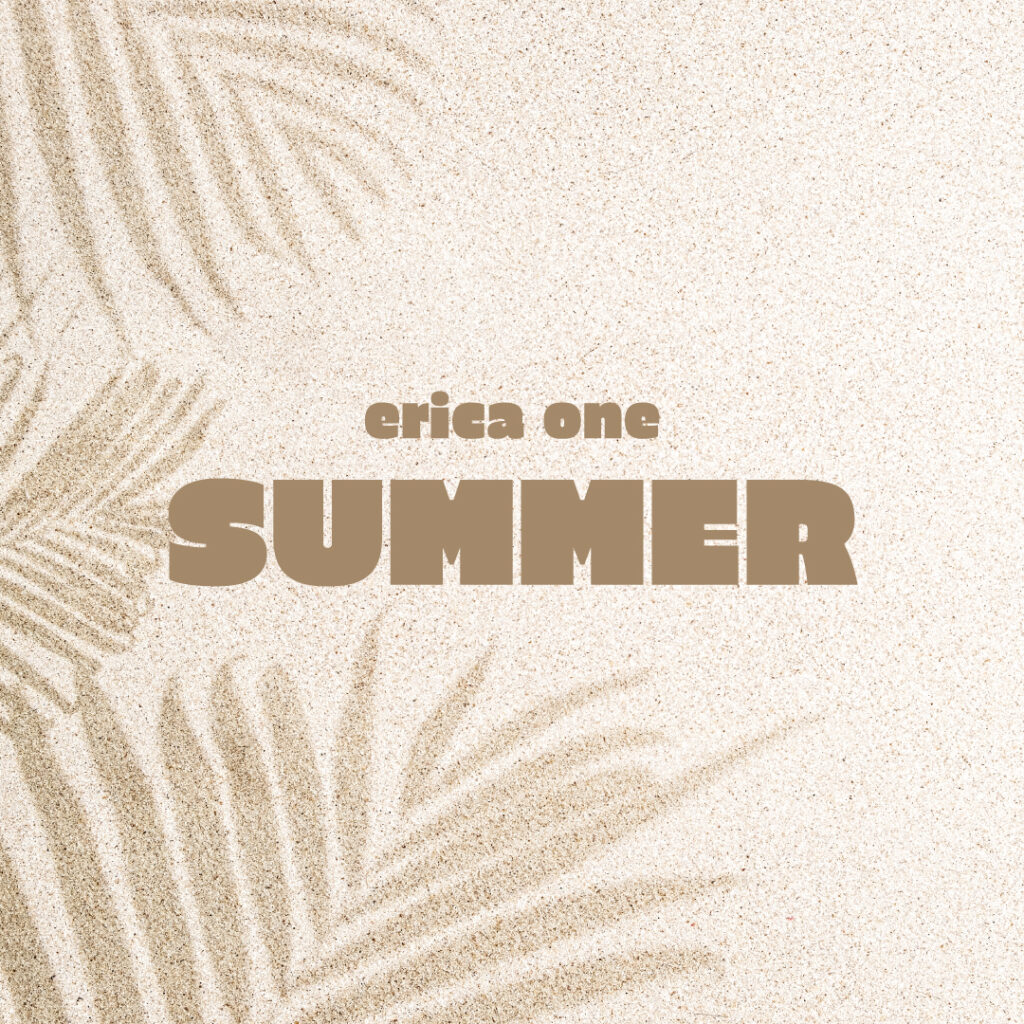
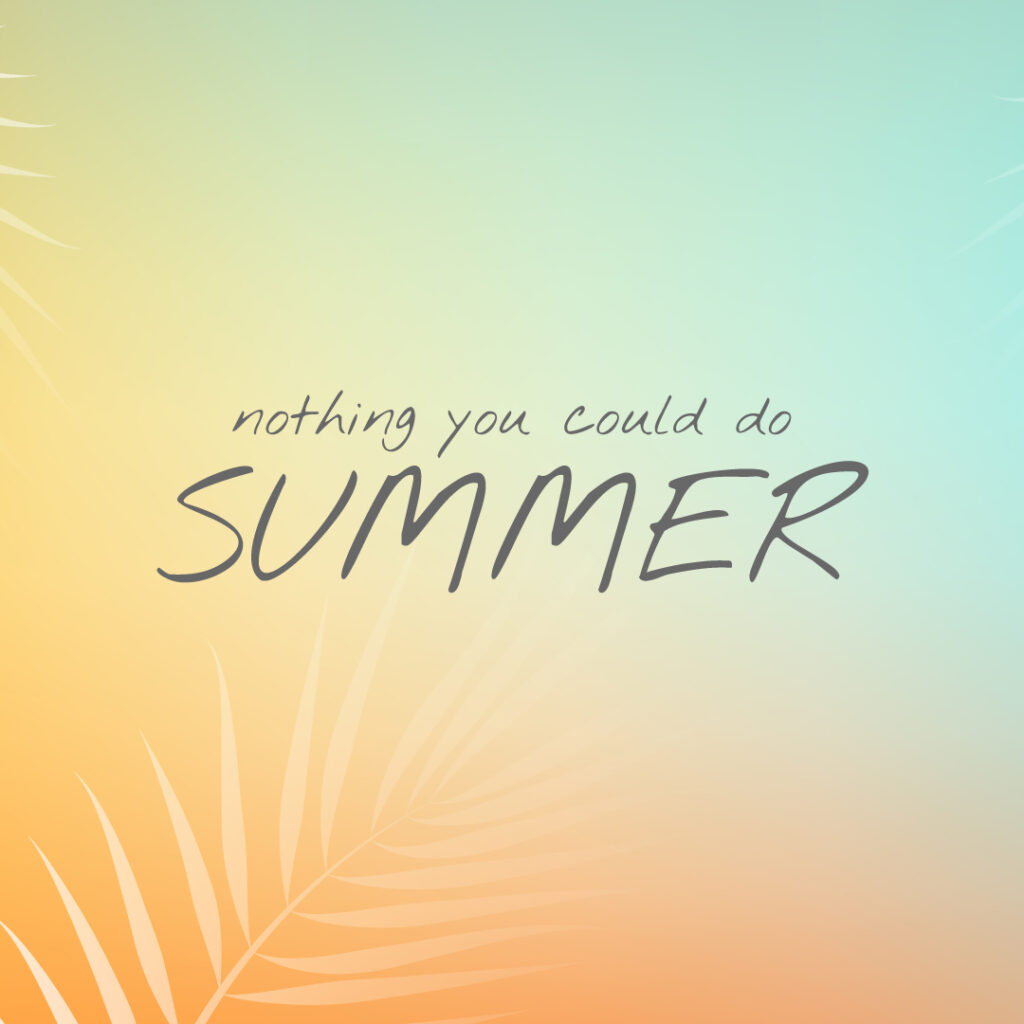
2. Nothing You Could Do – Letra a mano
Perfecta para: tarjetas postales, papelería, firmas manuscritas
Una tipo manuscrita natural y fluida, como una nota garabateada junto al mar. Ideal para aportar un toque humano.
3. Barlow Condensed – Deportiva y dinámica
Perfecta para: pósteres de gran formato, soportes de gran formato, títulos llamativos
Compacta, moderna y muy legible, Barlow Condensded aporta ritmo a tus diseños manteniendo un estilo limpio y ordenado.
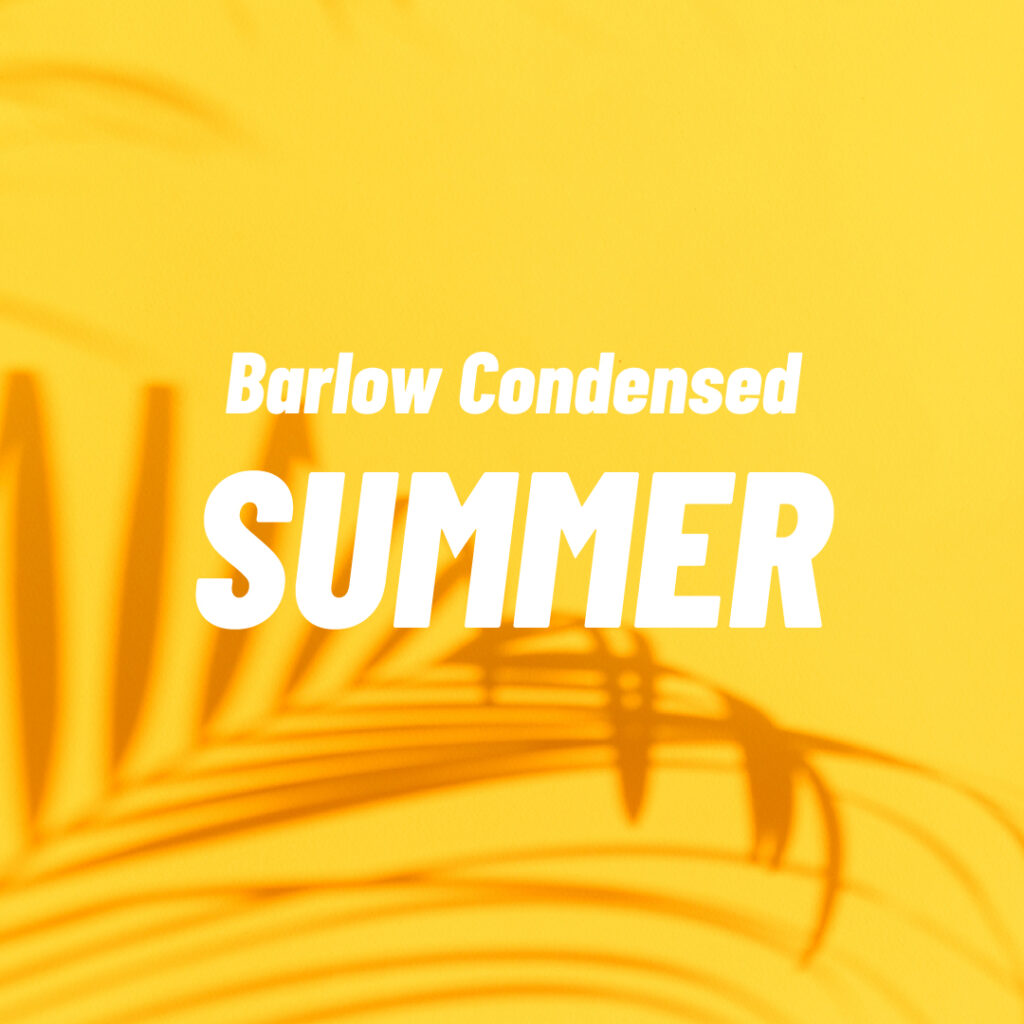
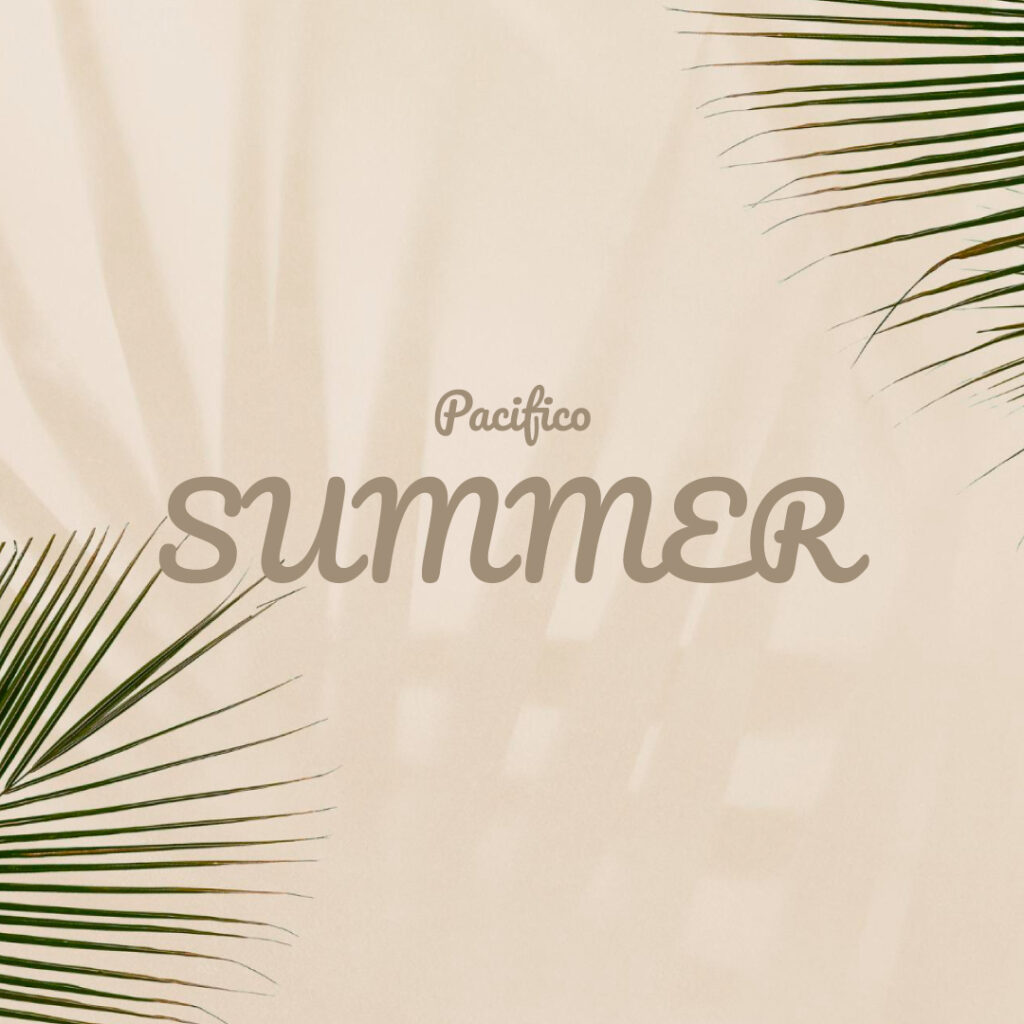
4. Pacifico – Muy veraniega
Perfecta para: comida, lifestyle, branding casual
Inspirada en los letreros retro de California, Pacifico transmite buen rollo al instante. Ideal para una identidad de marca con estilo feel-good.
5. Bungee – La tipografía que rompe
Perfecta para: pósteres urbanos, gran formato, títulos divertidos
Con su estilo en negrita y vertical, Bungee está hecho para destacar. Perfecta para exteriores y grandes formatos.
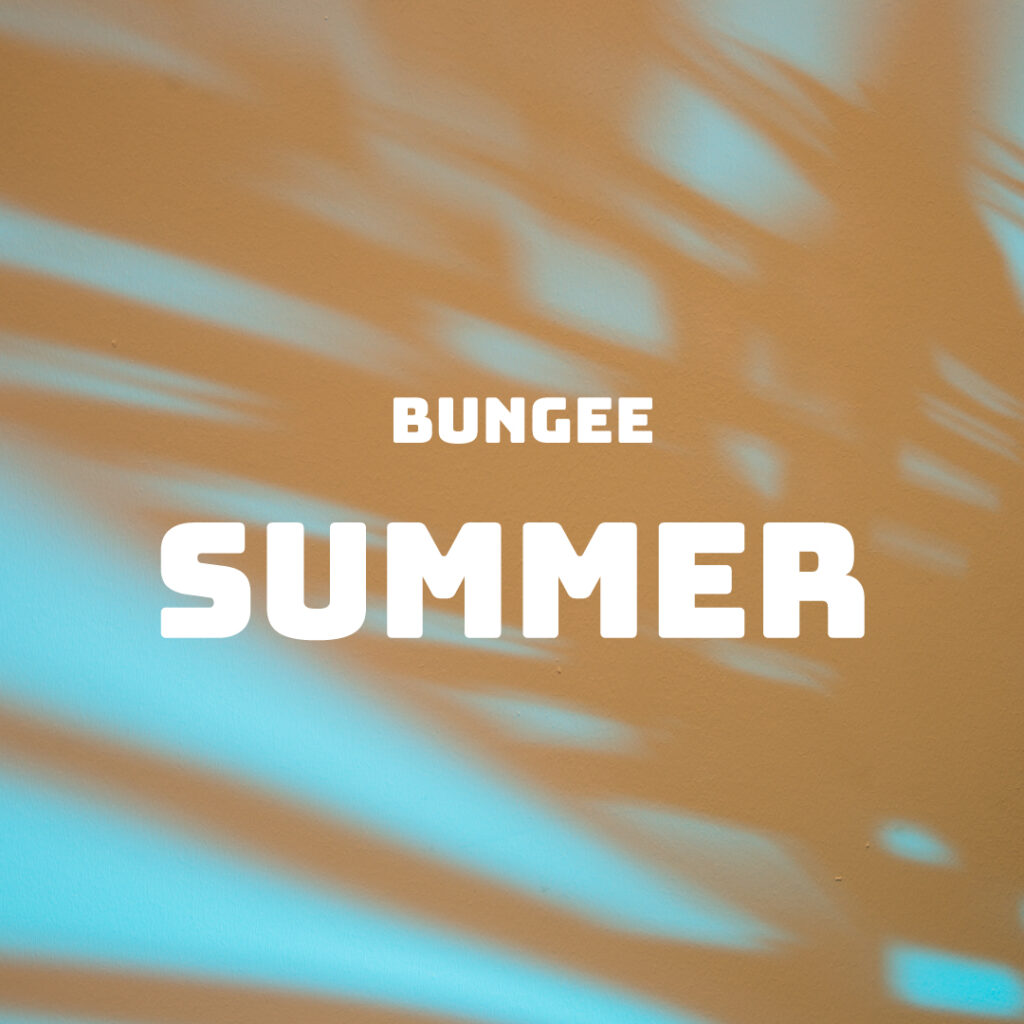
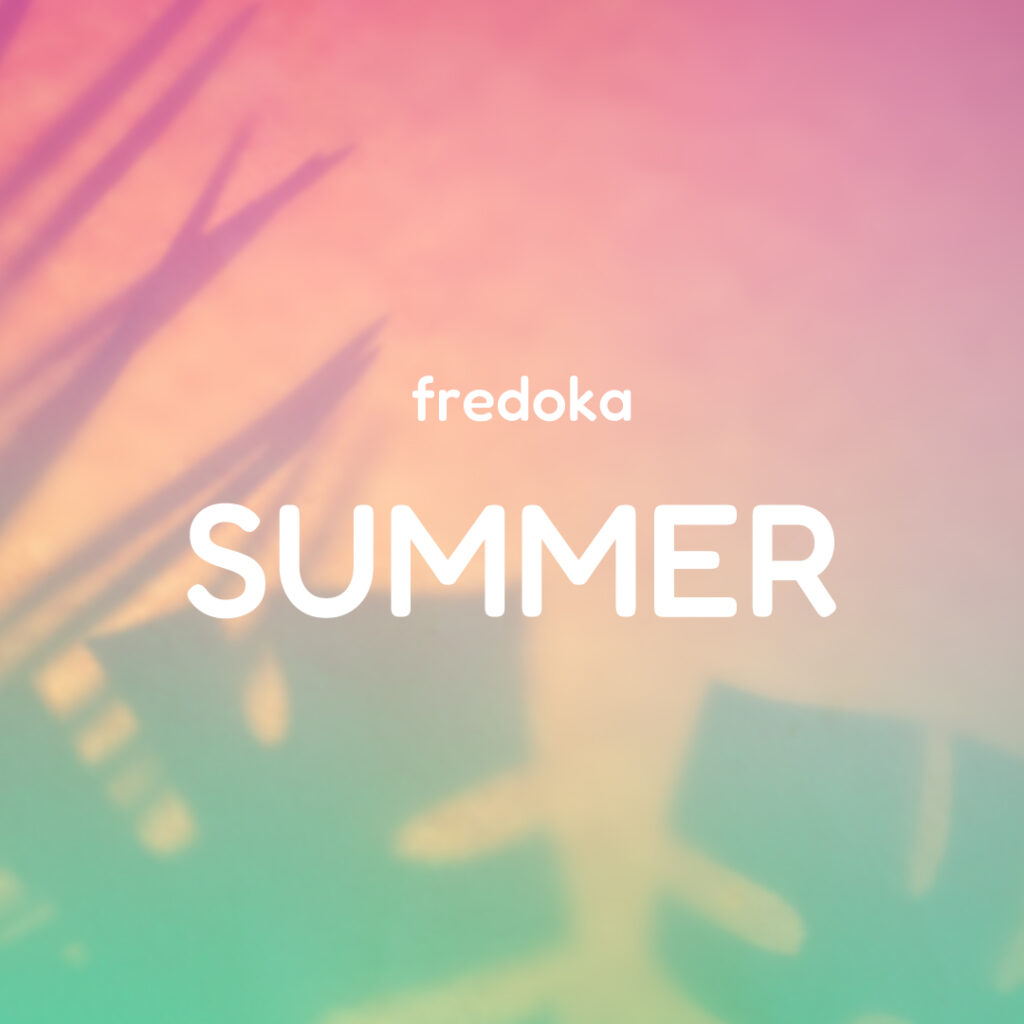
6. Fredoka – Redonda y accesible
Perfecta para menús, identidad visual de comida, comunicación infantil
Con sus letras redondeadas, Fredoka transmite cercanía y simpatía. Además, se lee perfectamente tanto en pantalla como en formato impreso.
7. Shrikhand – Atrevida
Perfecta para: branding original, packaging, pósteres de festival
Entre lo vintage y lo cartoon, Shrikhand tiene una presencia gráfica única. Por sí sola, viste cualquier título.
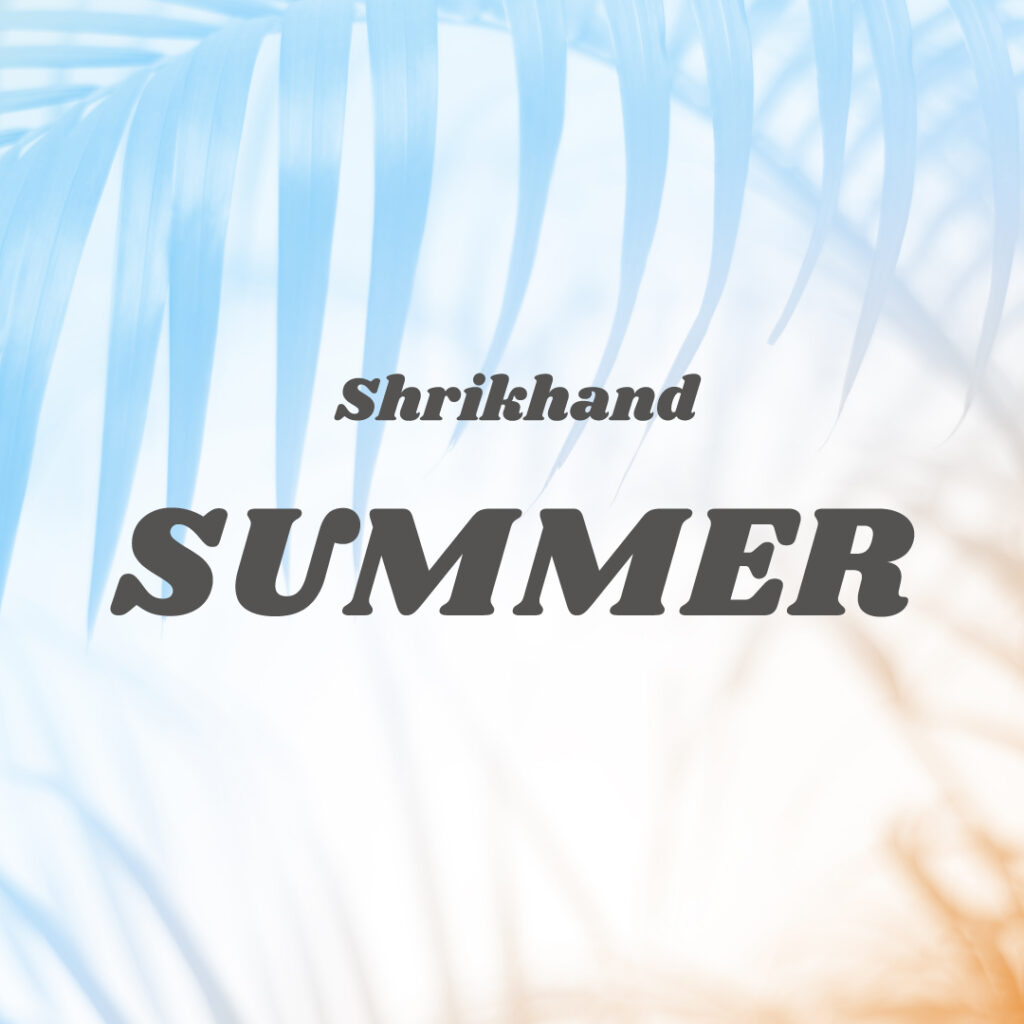
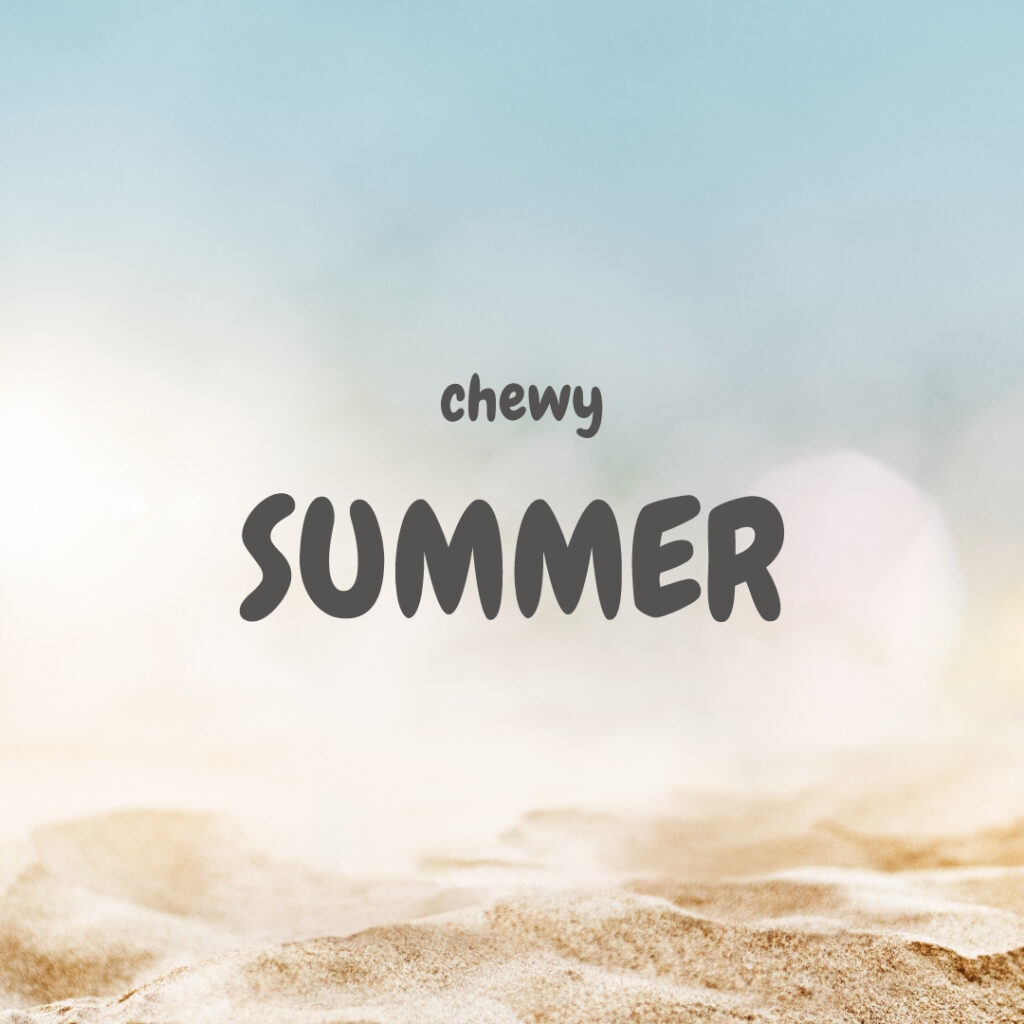
8. Chewy – Golosa
Perfecta para: snacks, helados, restaurantes familiares
Inspirada en tipografías de comics, Chewy es lúdica, generosa y alegre. Para usar sin moderación en tus creaciones veraniegas.
9. Poiret One – Elegante
Perfecta para: papelería elegante, diseño editorial, comunicación de eventos
Fina y minimalista, Poiret One ofrece un estilo que combina lo retro con lo sofisticado. Aporta mucho con muy poco.
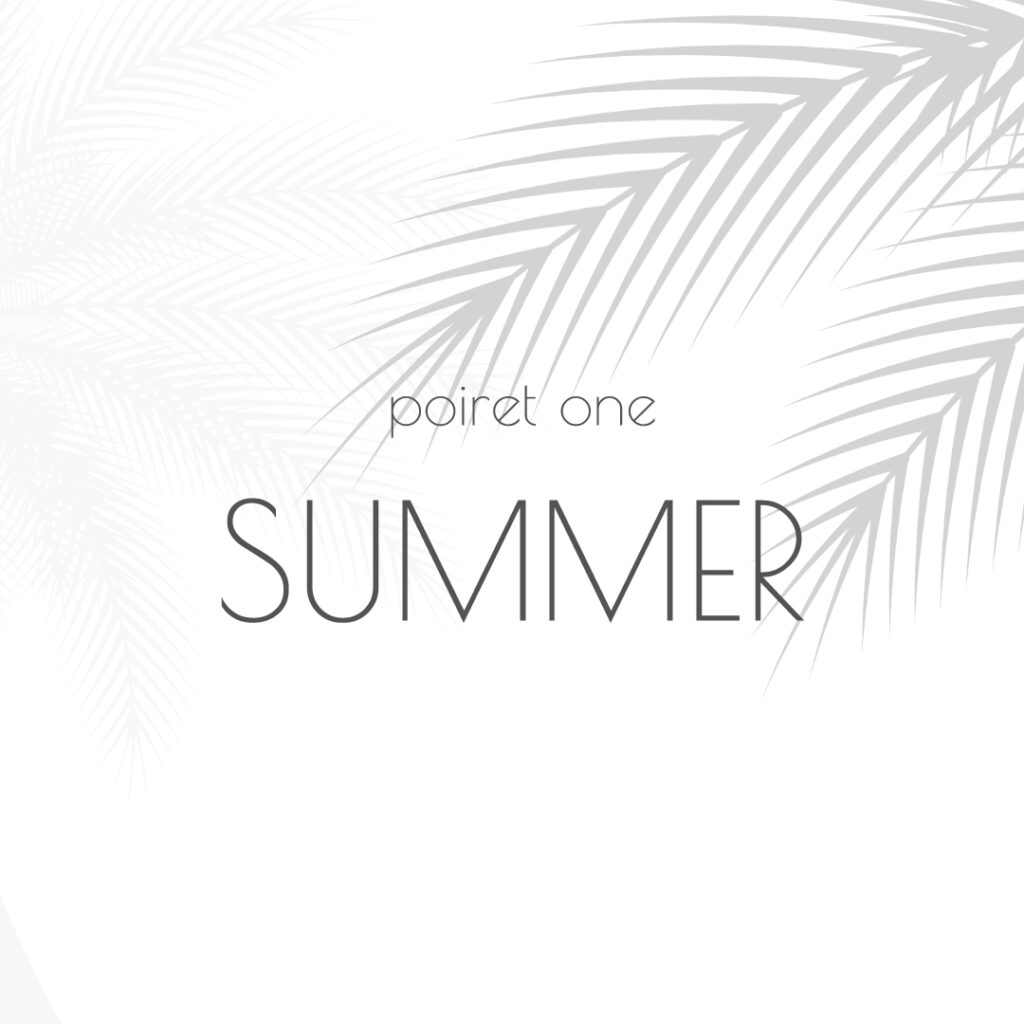
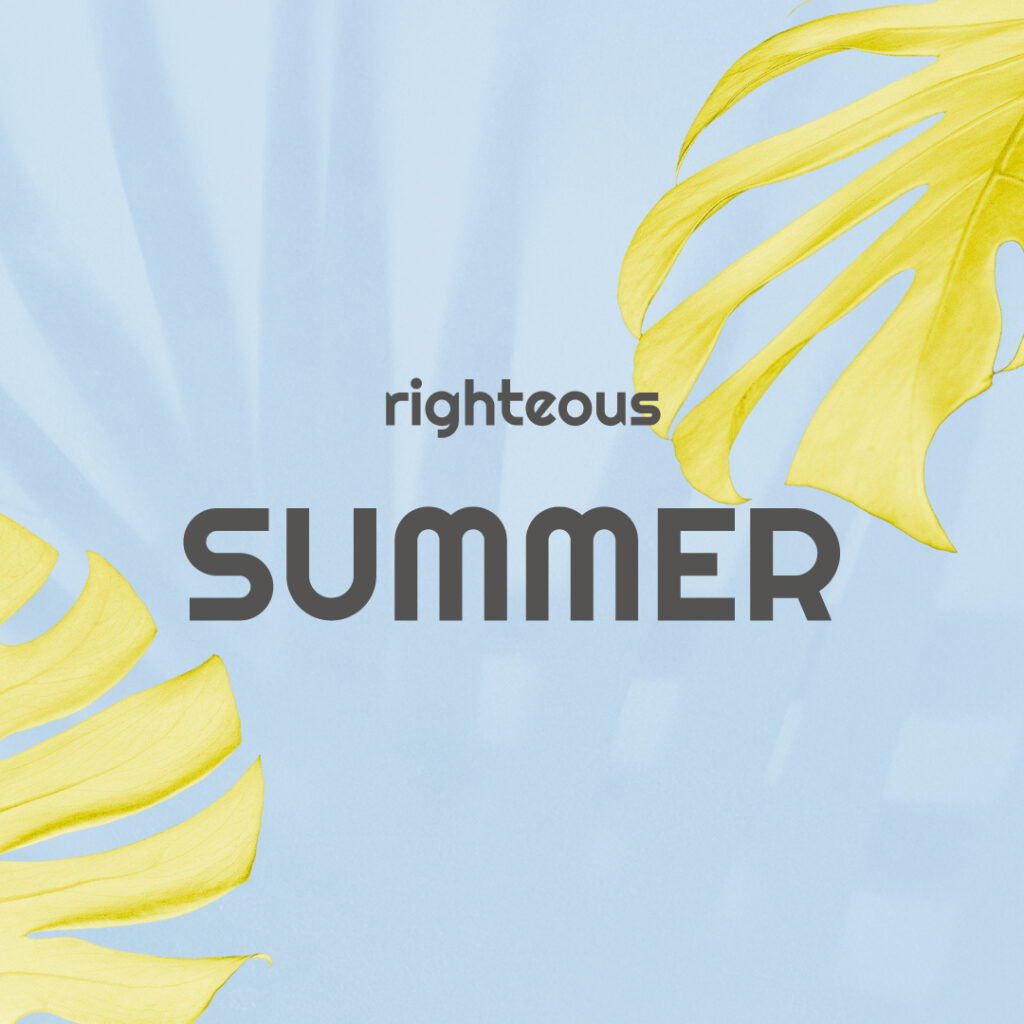
10. Righteous – Futurista y redondeada
Perfecta para: tecnología, pósteres pop, diseños innovadores
Con sus curvas geométricas y su estilo de ciencia ficción en tonos pastel, Righteous es original sin sacrificar legibilidad. Un buen equilibrio.